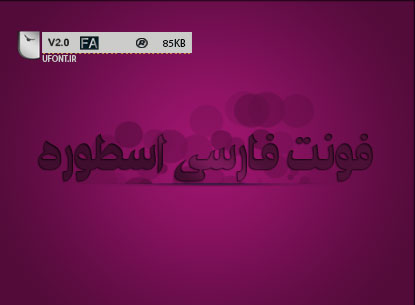
دانلود فونت فارسی اسطوره ، فونت فارسی جدید با ساختار فانتزی و نه چندان رسمی که بیشتر برای طرح های کودکانه می تواند مورد استفاده قرار بگیرد ، این فونت فانتزی فارسی هم اکنون بصورت رایگان از یوفونت منتشر می گردد
این فونت را میتوان برای طراحی هایی که مربوط به کودکان است بکار برد البته انتخاب این فونت برای متن مطمئنا کار صحیحی نیست چرا که در استفاده متن و نوشته های طولانی موجب اذیت چشم می شود و بیشتر برای عنوان پوسترها و عتواوین طرح های گرافیکی بکار می آید